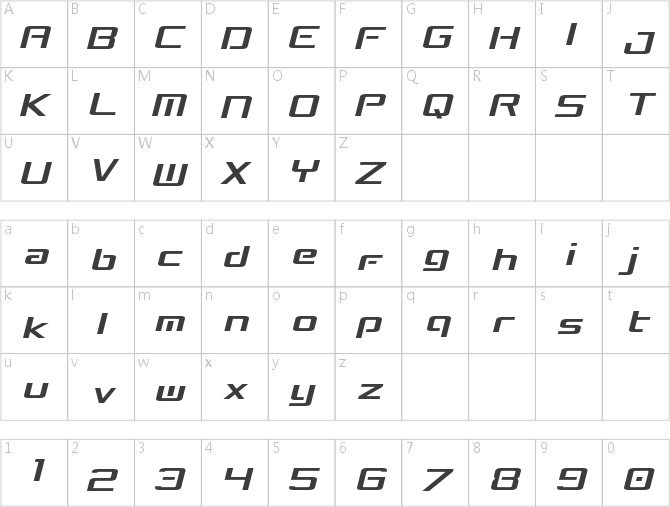
字体名称: Conciel
Concielian Break Condensed Semi
Concielian Break Condensed Semi介绍
Concielian Break Condensed Semi字体字库是一款让人赏心悦目、百看不厌的英文字体,适合各类广告和产品包装设计应用,字体大小0.03MB,格式为ttf字体,上传用户是青柠檬,作者/版权方为未知
Concielian Break Condensed Semi效果图